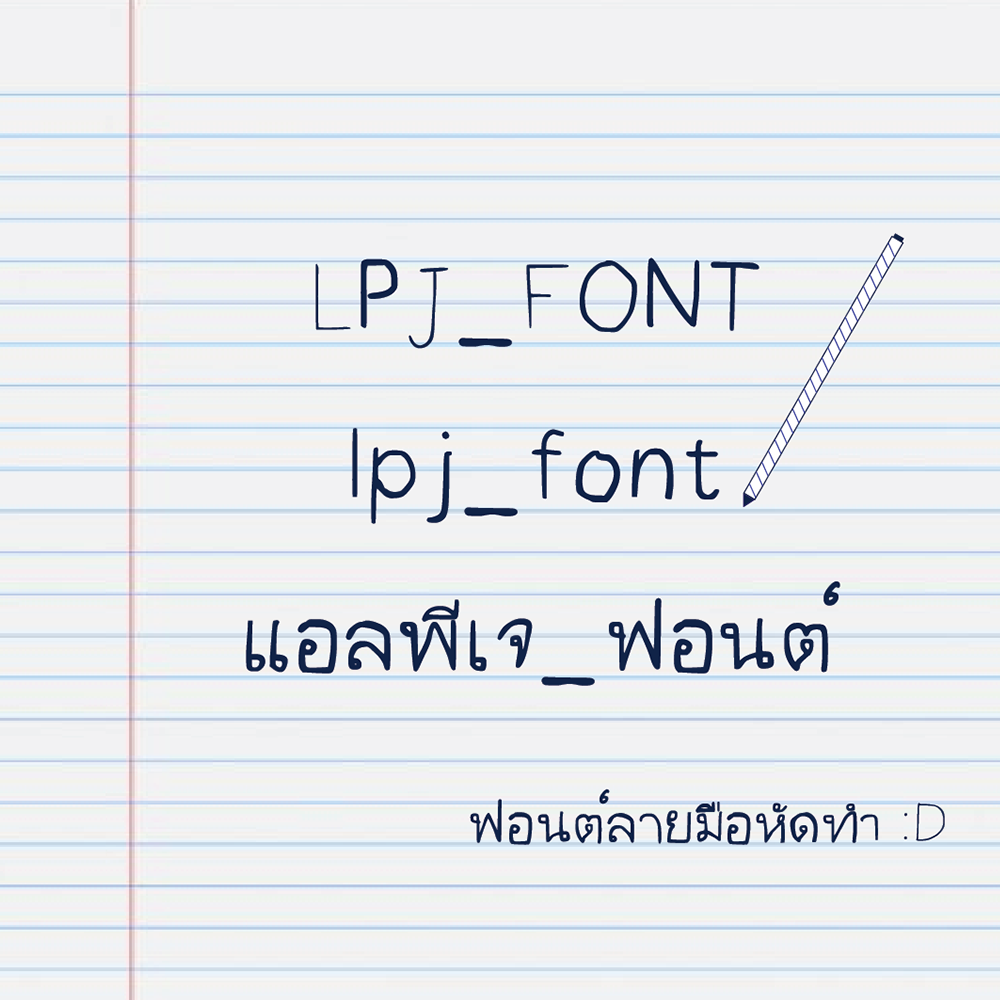
ฟอนต์ลายมือ lpj-font1
ชื่อฟอนต์ : Lpj_font1
หัดทำครั้งแรกนะครับมีอะไรอยากให้แก้ไขหรือปรับตรงไหนบอกได้นะครับ ส่วนอันนี้เป็นฟอนตฺลานมือนะครับ
น่ารักครับ พอมันไม่สม่ำเสมอกันแล้วดูเป็นธรรมชาติดี
แต่ฟอนต์นี้ยังไม่ได้แก้เรื่องวรรณยุกต์ใช่ไหมครับ
ใช่ครับตอนนี้ กำลังหัดทำและปรับปรุงแก้ไขครับ